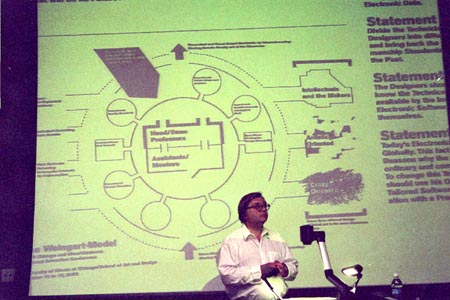
Wolfgang Weingart (1941 -)Tipógrafo e formador suíço, um dos papas do «Estilo Internacional». Altamento esquemático e tedioso, como a maioria dos outros protagonistas da Escola Suíça.
As experiências de Wolfgang Weingart na Escola de Tipografia da Basiléia, no ano de 1968, marcaram o início de uma nova atitude no design gráfico. A tradicional Escola passou a considerar as possibilidades da improvisação e da experimentação tipográfica. A segunda vaga do Descontrutivismo Tipográfico apareceu na Suíça dos anos 60 - o país modelo do desenho gráfico, do Estilo Internacional, o país afogado no dogmatismo dos mestres de Zürich e Basel. Wolfgang Weingarten, ele próprio suíço, foi o primeiro a incitar à ultrapassagem da estéril perfeição do Estilo Internacional. No seu ensaio publicado em 1976 na revista Typographische Monatsblätter, Weingarten apelou à insurreição contra o dogmatismo sufocador apregoado pelos puritanos Josef Müller- Brockmann, Emil Ruder e Armin Hoffmann. Na década de 1980, já ninguém falava de Weingarten, pois a atracção vinha dos designers punk; vinha de Londres. Aparece a terceira vaga do Desconstrutivismo; o seu impulsionador foi o grande designer gráfico que é Neville Brody. Um designer que começou com a imagem do rebelde para em poucos anos se converter num dos mais aclamados designers do mainstream na sua vertente lifestyle. Wolfgang Weingart completed his typesetting apprenticeship in hand composition in 1963. He taught typography at the University of Art and Design Basel from 1968 to 2004 and, at the invitation of Armin Hofmann, was an instructor during the Yale Summer Program in Graphic Design in Brissago from 1974 through 1996. Nos últimos 30 anos, Weingart deu palestras e leccionou em muitos países da Europa, das Américas, da Ásia e da Austrália. Entretanto está representado nas Coleccções permanentes de Museus e galerias privadas.
Weingart foi membro da Alliance Graphique Internationale/AGI desde 1978 até 1999, e co-editor dos Typographische Monatsblätter de 1970 até 1988. O trabalho gráfico de Weingart é marcado pelo espaçamento diferenciado entre os caracteres, em regra muito largo. A sua tipografia baseou-se em estudos de semântica, da sintaxe e da funcionalidade da tipografia. Enquanto a tipografia da Escola Suíça se tinha imobilizado na asquetismo, Weingart estava mais interessado em fazer valer as qualidades gráficas da tipografia. Acreditava que certas alterações gráficas nos caracteres poderiam intensificar a mensagem textual e visual de um poster. Hoje, Weingart criou o seu workshop em Basel. Curso em Julho de 2007: Basics in Design and Typography basics.sfgbasel.ch Temas relacionadosPreferências tipográficas de WW